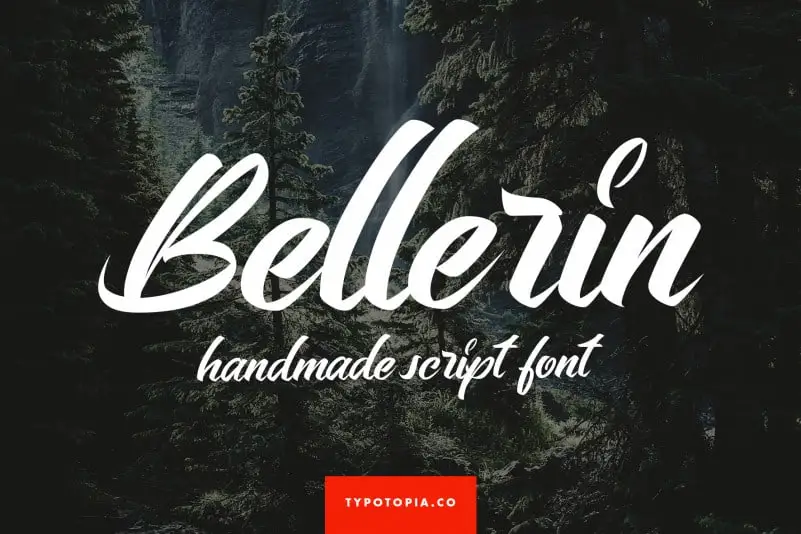
Bellerin Handmade Script Font – Download Grátis
A Bellerin Handmade Script Font é uma novidade que traz uma mistura única e moderna entre estilo gótico e letra feita às mãos com um toque casual. Essa fonte vem diretamente do ateliê de typotopia, oferecendo designers e criativos a oportunidade de adicionar um toque único à suas criações digitais. Se você busca uma fonte que combine elegância moderna com um estilo quase artesanal, então Bellerin é perfeito para você. Suas letras fluidas expressam tanto sofisticação quanto descontraído charme, tornando-a uma opção ideal para qualquer projeto que valorize o detalhe e a personalização. Estamos ansiosos para ver os designs criados com esta fonte, pois ela oferece um meio perfeito de unir elegância moderna com um toque pessoal. Se você está procurando por uma nova fonte para seus projetos digitais, Bellerin é uma opção que merece consideração.